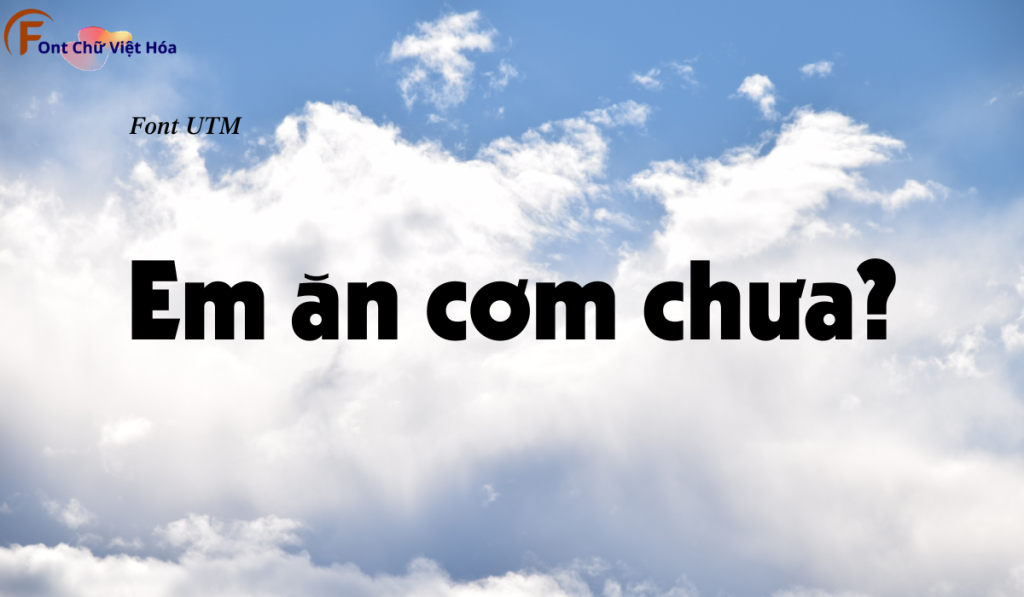
Font UTM Kabel Kt Việt Hóa
Kiểu chữ: Sans-serif
Font UTM Kabel Kt Việt Hóa là một font chữ không chân mạnh mẽ, thuộc bộ font UTM. Được thiết kế với mục tiêu mang lại sự hiện đại và năng động, font này lý tưởng cho các dự án thiết kế như logo, poster, và bao bì sản phẩm. Với các nét chữ rõ ràng và độ dày đều đặn, Font UTM Kabel Kt Việt Hóa không chỉ dễ đọc mà còn tạo cảm giác mạnh mẽ và hiện đại. Việc Việt hóa font giúp người dùng dễ dàng tích hợp vào các thiết kế tiếng Việt, mang lại sự tiện lợi và nâng cao tính thẩm mỹ.